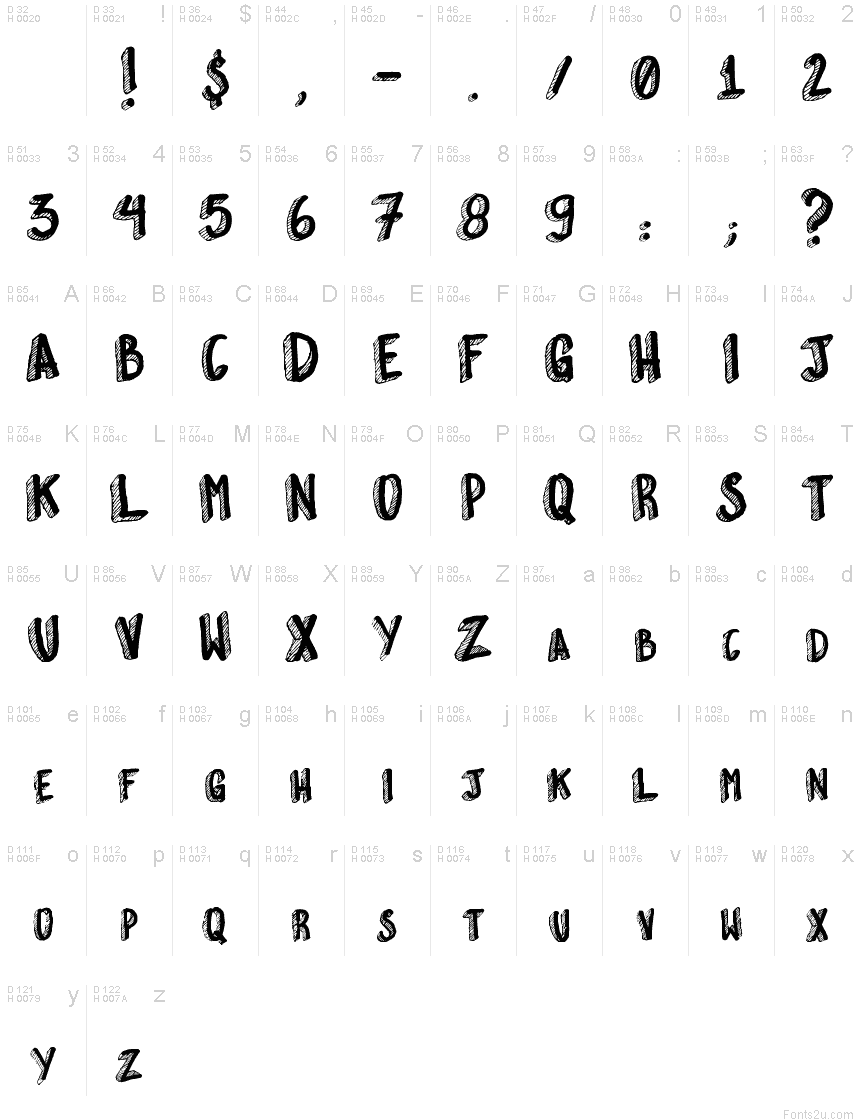
Esquisito to darmowy, ręcznie rysowany font typu display o surowym, komiksowym charakterze. Litery wyglądają, jakby zostały szybko nakreślone pędzlem i wypełnione ukośnym szrafowaniem. Nadaje to całemu krojowi żywą, szkicową teksturę i nieco nieoczywisty rytm, który sprawia wrażenie naturalnego, a nie wygładzonego.
Świetnie sprawdzi się na plakatach, w zinach, na okładkach książek dla dzieci, opakowaniach, menu kawiarnianych i kartach tytułowych, gdzie ta bazgrołowata energia wzmacnia przekaz. Jako darmowy font sprawdza się również w krótkich nagłówkach, nazwach zespołów i zabawnych projektach brandingowych, ponieważ kreskowane wypełnienie i drżące kontury nadają charakteru nawet pojedynczym literom.
Esquisito